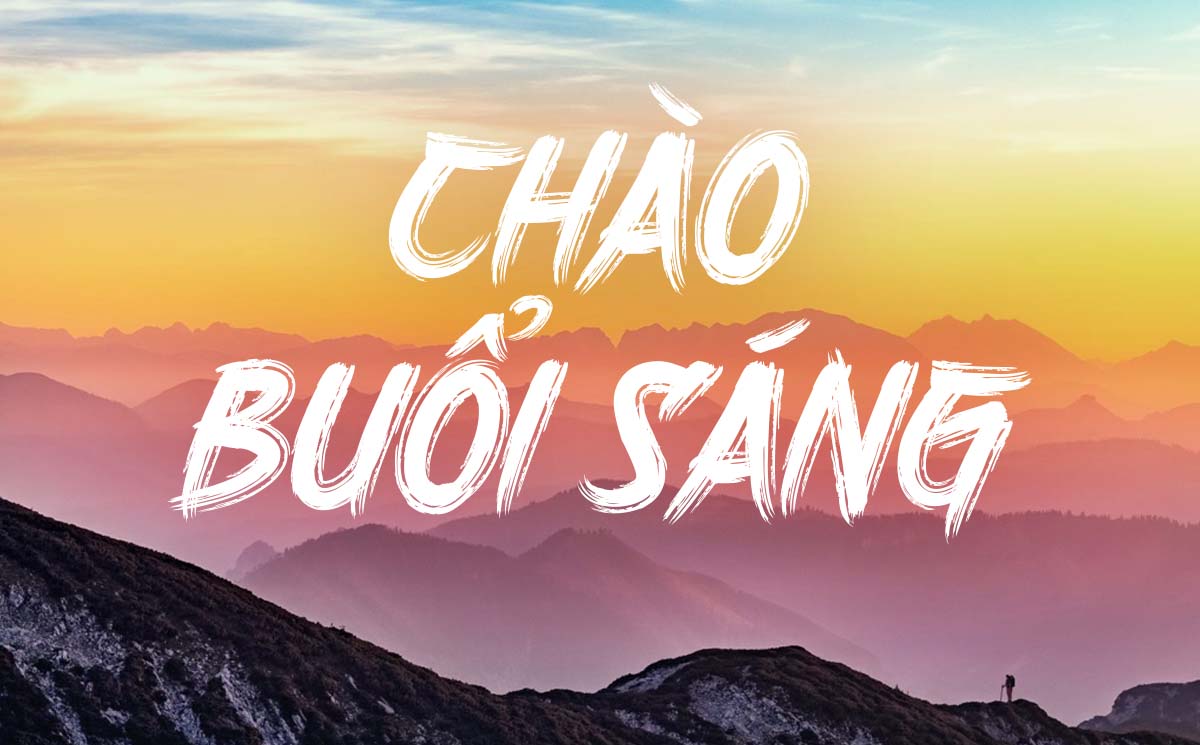
SVN DHF Harry’s Brush Việt hóa là font chữ brush miễn phí nổi bật với những đường nét cọ mạnh mẽ, phóng khoáng và giàu cảm xúc. Kiểu chữ mang vẻ đẹp thủ công tự nhiên, phù hợp với các thiết kế cần tạo ấn tượng cá tính như poster, tiêu đề, banner, logo, bao bì, nội dung mạng xã hội và nhiều sản phẩm sáng tạo khác.
Nhờ được Việt hóa, font hỗ trợ tốt hơn cho nội dung tiếng Việt có dấu, giúp nhà thiết kế, người làm nội dung và chủ thương hiệu dễ dàng ứng dụng vào các dự án trong nước. Nếu bạn đang tìm một font chữ nét cọ vừa nghệ thuật, dễ sử dụng, vừa tạo được điểm nhấn thị giác mạnh thì SVN DHF Harry’s Brush là lựa chọn đáng cân nhắc.
Font chữ brush nét cọ miễn phí SVN DHF Harry’s Brush Việt hóa mô phỏng chuyển động của những nét cọ được viết bằng tay. Các ký tự không quá cứng nhắc mà có sự thay đổi linh hoạt về độ dày, độ nghiêng và hình dáng, từ đó tạo nên cảm giác chân thực như được vẽ trực tiếp trên bề mặt thiết kế.
Phong cách của font là sự kết hợp giữa chất nghệ thuật, nét bụi bặm và tinh thần tự do. Đây là một lựa chọn phù hợp khi bạn muốn nội dung chữ không chỉ truyền tải thông tin mà còn đóng vai trò như một yếu tố đồ họa trung tâm. Font có thể được sử dụng độc lập cho những dòng tiêu đề ngắn hoặc kết hợp với các kiểu chữ sans serif đơn giản để tạo ra bố cục cân bằng, dễ đọc.
Thiết kế nét cọ thủ công mạnh mẽ và giàu cảm xúc
Điểm nổi bật nhất của SVN DHF Harry’s Brush nằm ở hình dáng ký tự được xây dựng theo phong cách brush lettering. Từng nét chữ có độ chuyển động rõ ràng, mô phỏng dấu vết của đầu cọ khi lướt trên giấy. Sự không đồng đều có chủ ý giữa các nét thanh, nét đậm và phần kết thúc ký tự giúp font giữ được vẻ tự nhiên thay vì tạo cảm giác máy móc.
Nhờ ngôn ngữ tạo hình mạnh, font có khả năng thu hút ánh nhìn ngay từ những giây đầu tiên. Bạn có thể sử dụng font để nhấn mạnh tên chiến dịch, khẩu hiệu, thông điệp quảng cáo hoặc những câu trích dẫn truyền cảm hứng. Phong cách này đặc biệt phù hợp với các chủ đề liên quan đến sáng tạo, thể thao, thời trang đường phố, du lịch, âm nhạc, ẩm thực, sự kiện và phong cách sống.
Hỗ trợ tiếng Việt, thuận tiện cho nhiều nội dung trong nước
Phiên bản SVN DHF Harry’s Brush Việt hóa được bổ sung hệ thống ký tự cần thiết để trình bày nội dung tiếng Việt. Người dùng có thể nhập các nguyên âm có dấu, phụ âm đặc trưng và nhiều tổ hợp dấu phổ biến mà không phải chỉnh sửa thủ công từng ký tự. Điều này giúp quá trình thiết kế tiêu đề, slogan hoặc tên sản phẩm bằng tiếng Việt trở nên nhanh chóng và đồng bộ hơn.
Khả năng hiển thị tiếng Việt là một ưu điểm quan trọng đối với nhà thiết kế, cửa hàng trực tuyến, đơn vị truyền thông và người sáng tạo nội dung. Thay vì phải ghép dấu hoặc chuyển đổi sang hình ảnh, bạn có thể nhập văn bản trực tiếp trong phần mềm, sau đó thay đổi kích thước, màu sắc, khoảng cách và hiệu ứng theo nhu cầu. Trước khi xuất bản, người dùng vẫn nên kiểm tra toàn bộ dấu câu và ký tự trên phần mềm đang sử dụng để bảo đảm kết quả hiển thị chính xác.
Ứng dụng linh hoạt trong thiết kế truyền thông và nhận diện
SVN DHF Harry’s Brush có thể xuất hiện trong nhiều loại sản phẩm khác nhau, từ thiết kế kỹ thuật số đến ấn phẩm in. Với những dự án cần sự trẻ trung và cá tính, font giúp phần chữ trở thành điểm nhấn nổi bật mà không cần thêm quá nhiều chi tiết trang trí. Một số ứng dụng phù hợp gồm:
- Thiết kế poster sự kiện, banner quảng cáo, ảnh bìa và thumbnail video.
- Trình bày slogan, câu trích dẫn, tiêu đề bài đăng và nội dung trên mạng xã hội.
- Sáng tạo logo dạng chữ, tên thương hiệu hoặc bộ nhận diện mang phong cách thủ công.
- Thiết kế bao bì thực phẩm, nhãn sản phẩm, menu quán cà phê và tài liệu quảng bá.
- Trang trí áo thun, sticker, thiệp mời, bìa sách, bìa album và sản phẩm in theo yêu cầu.
Do có cá tính thị giác khá mạnh, font phát huy hiệu quả nhất khi được dùng cho tiêu đề hoặc nội dung ngắn. Đối với đoạn văn dài, bạn nên kết hợp SVN DHF Harry’s Brush với một font dễ đọc hơn. Cách phối hợp này vừa duy trì điểm nhấn nghệ thuật, vừa bảo đảm người xem tiếp nhận thông tin thuận lợi trên cả màn hình máy tính và thiết bị di động.
Dễ phối hợp màu sắc, hiệu ứng và nhiều phong cách bố cục
Kiểu chữ nét cọ có ưu thế khi kết hợp với các hiệu ứng đồ họa như texture giấy, nền sơn, hạt nhiễu, viền chữ, đổ bóng hoặc chuyển màu. Tùy theo định hướng thiết kế, SVN DHF Harry’s Brush có thể mang vẻ sôi động, nổi loạn, cổ điển hoặc gần gũi. Chẳng hạn, chữ màu trắng trên nền tối tạo cảm giác mạnh mẽ; chữ đen trên nền giấy ngả màu gợi chất thủ công; còn các gam màu nóng giúp thiết kế trở nên trẻ trung và giàu năng lượng.
Khi dàn trang, bạn nên dành đủ khoảng trống xung quanh tiêu đề để các nét cọ được thể hiện rõ ràng. Hạn chế sử dụng quá nhiều hiệu ứng cùng lúc vì điều này có thể làm giảm tính tự nhiên của font. Nếu cần xây dựng hệ thống phân cấp nội dung, hãy dùng SVN DHF Harry’s Brush cho thông điệp chính và chọn một font sans serif hoặc serif có hình dáng gọn gàng cho phần mô tả, thông tin liên hệ và nội dung chi tiết.